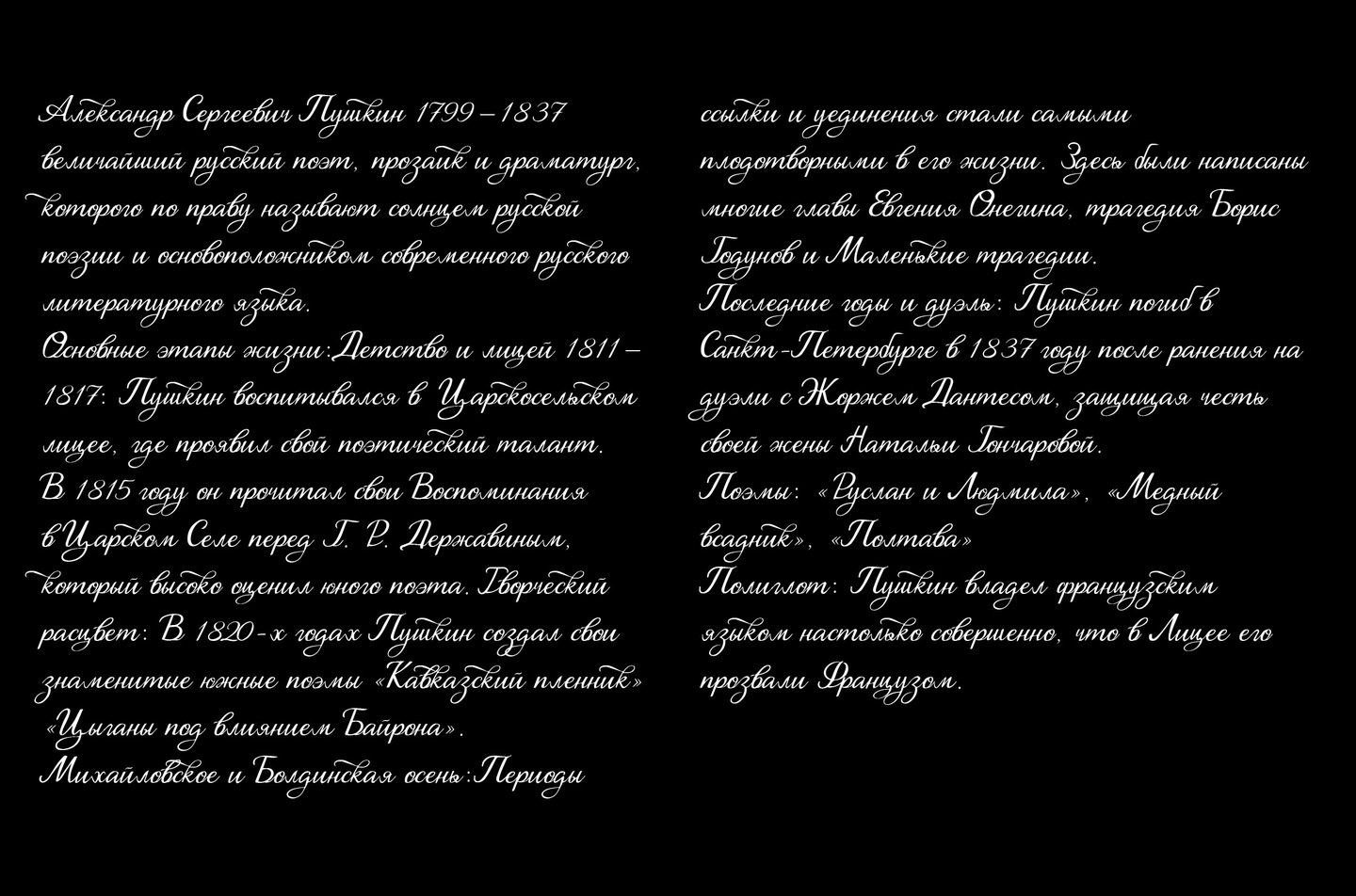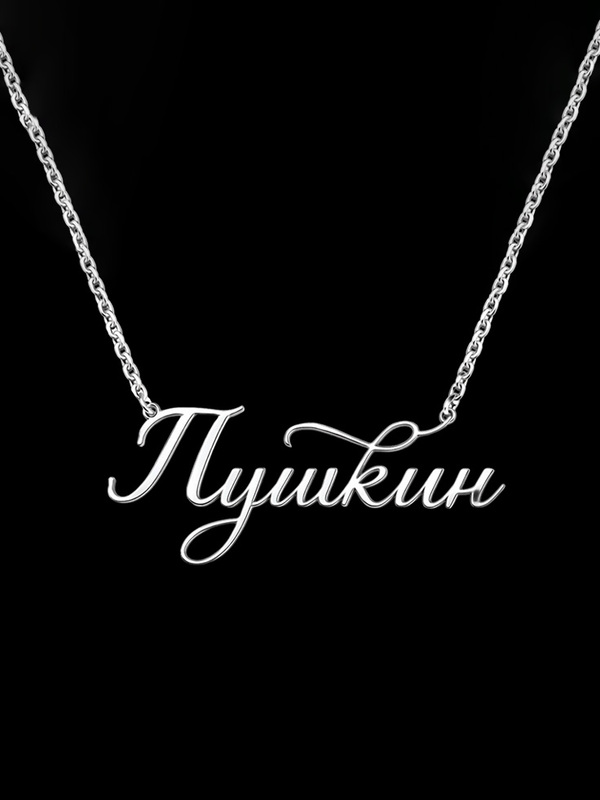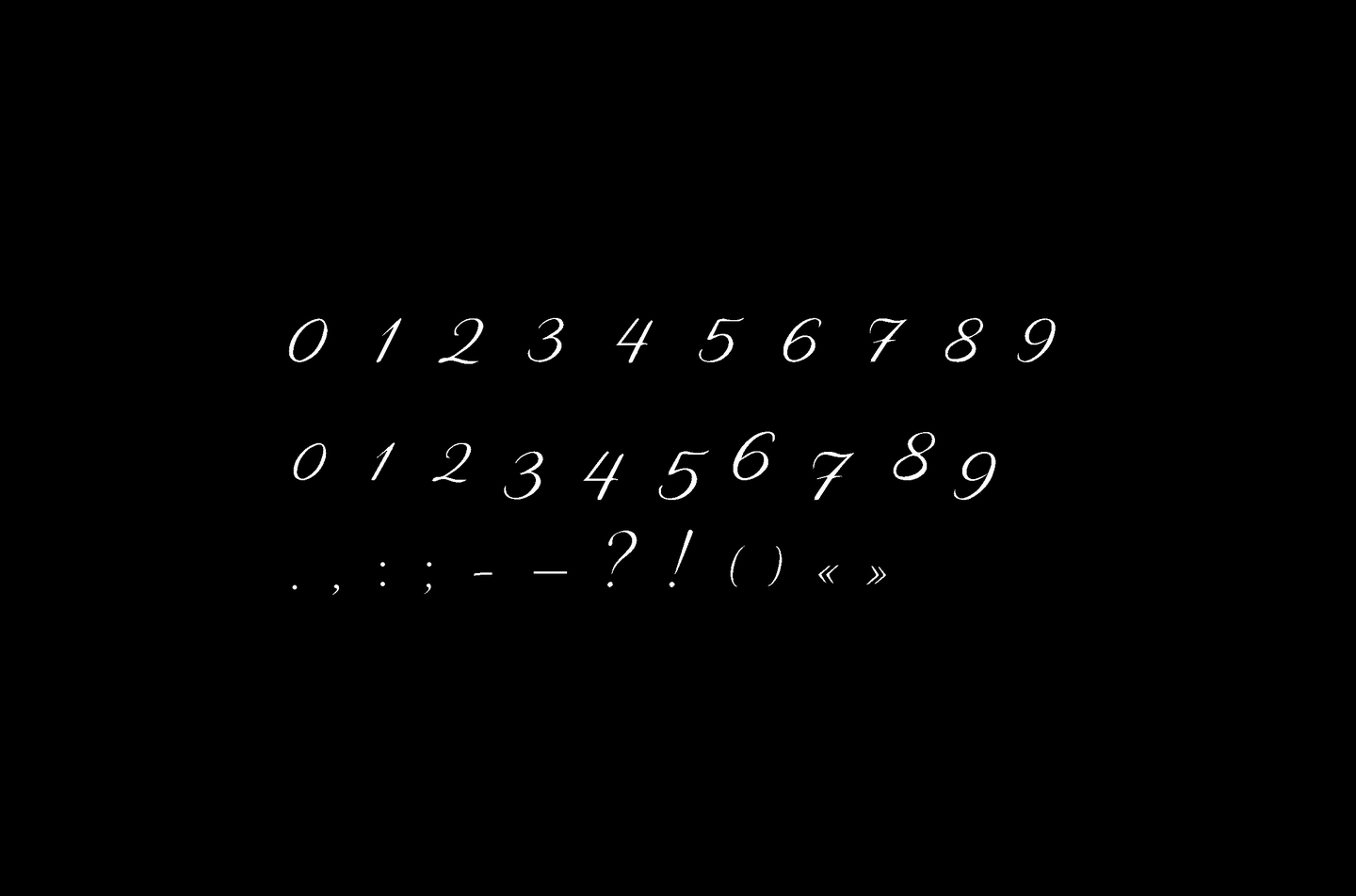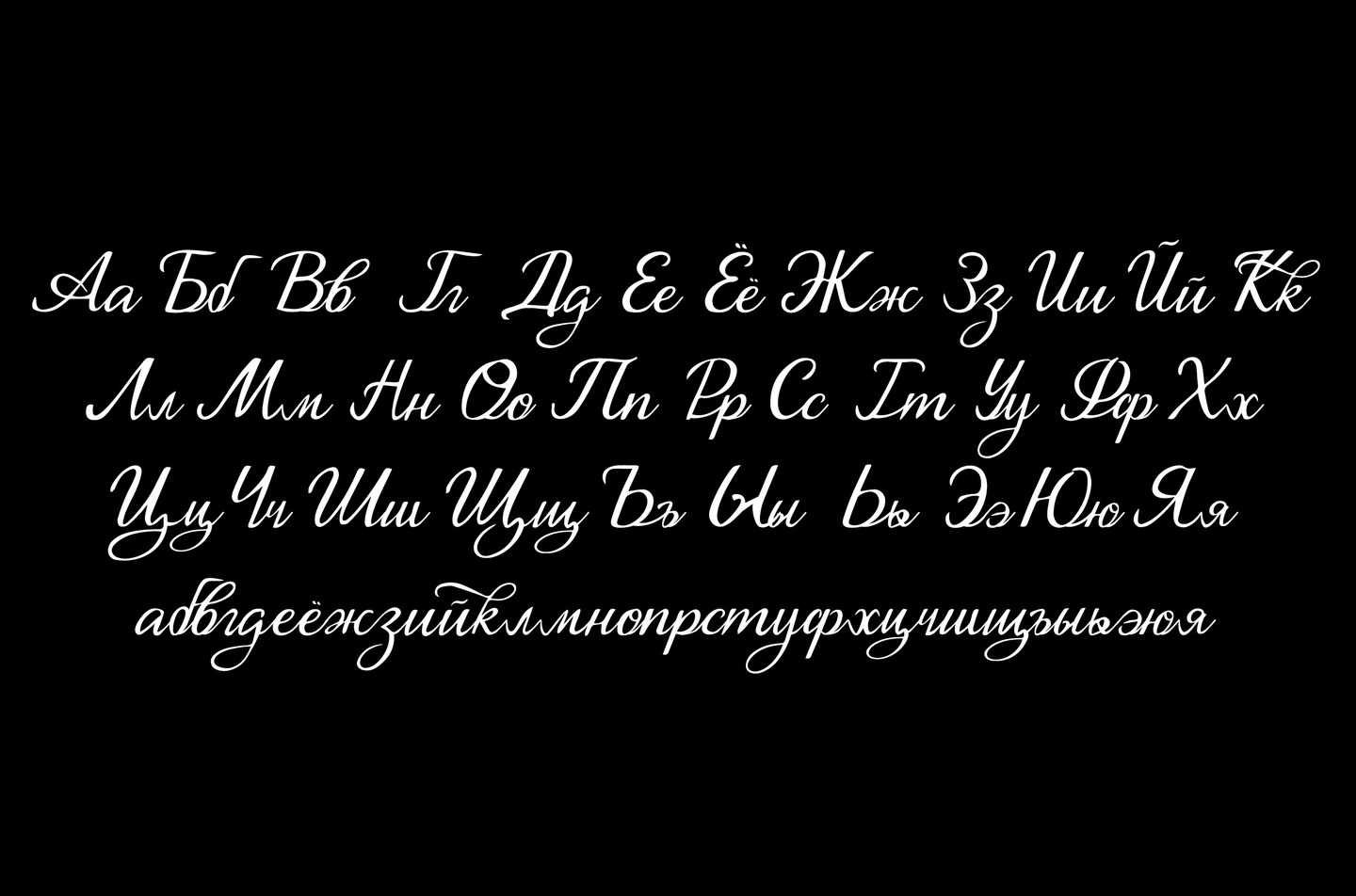
Шрифт под названием «Пушкин» получил своё имя не случайно — он вдохновлён богатым наследием классической литературы и эстетикой Золотого века русской культуры. Его изящные изгибы, плавные линии и необычная форма создают ощущение живого рукописного текста, словно перед глазами возникают черновики великих авторов, наполненные мыслями, эмоциями и творческим поиском.
В дополнение к шрифту была разработана уникальная коллекция украшений, которая продолжает ту же идею изысканности и культурного вдохновения. В неё вошли браслет, кулон, брошь и кольцо — каждый элемент выполнен с вниманием к деталям и отражает характерные черты шрифта «Пушкин». Эти украшения не только дополняют визуальную концепцию, но и превращают её в осязаемую форму, позволяя прикоснуться к эстетике классической литературы через современный дизайн.